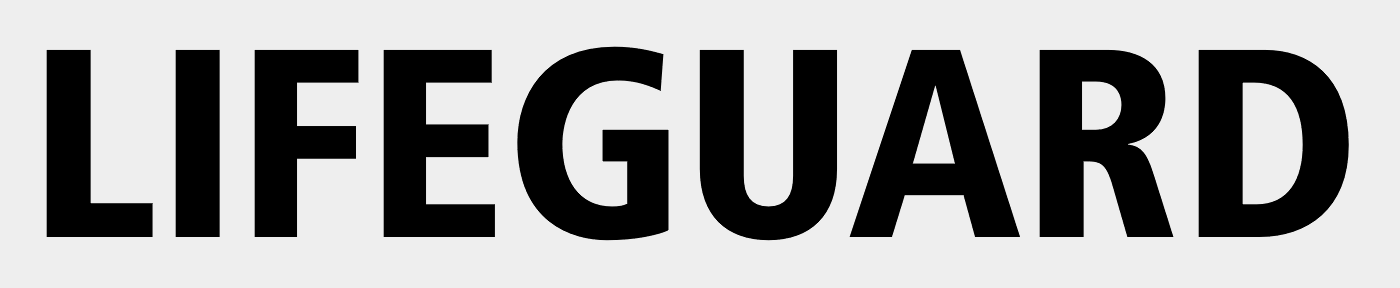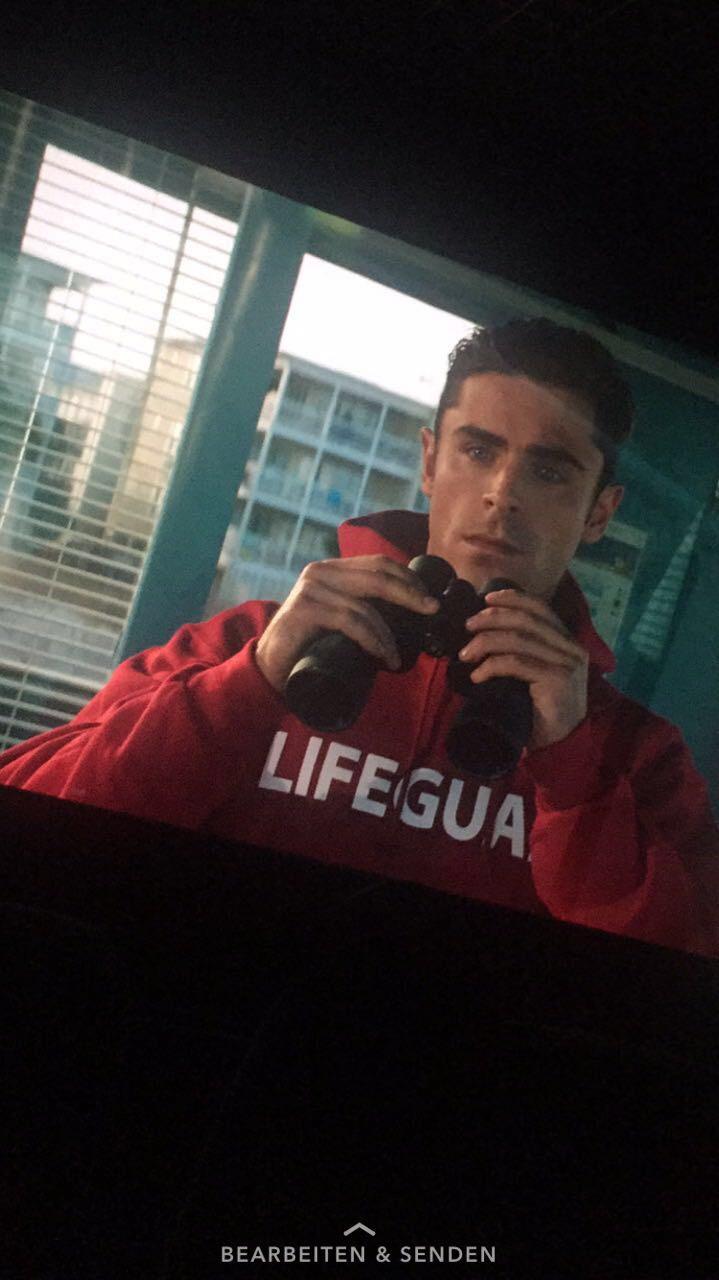
Suche Schriftart aus dem Film Baywatch (Lifeguard Hoodie)
ich war gestern in dem Film Baywatch und ein Hoodie mit dem Schriftzug Lifeguard hat es mir dabei besonders angetan.
Daher meine Frage, erkennt jemand eventuell die Schriftart  des Schriftzuges "Lifeguard" oder kennt eine gute Alternative, welche möglichst gleich aussieht?
Ich würde da auf die Avenir oder Frutiger tippen:
Edit: Du hast nicht zufällig ein Bild, auf dem der Schriftzug komplett zu sehen ist?
Vielen Lieben Dank, ich glaube die Fonts passen. :)
Nein leider habe ich kein Bild mit dem kompletten Schriftzug, da der Film aktuell ja noch im Kino anläuft ist es recht schwer überhaupt ein Bild zu finden. Trotzdem großartige Arbeit.
Wenn ich mir das R so anschau, passen die nicht sonderlich gut. Da wäre die Frutiger näher dran …
Ja anhand des "R" hätte ich auch Frutiger als am passendsten empfunden.